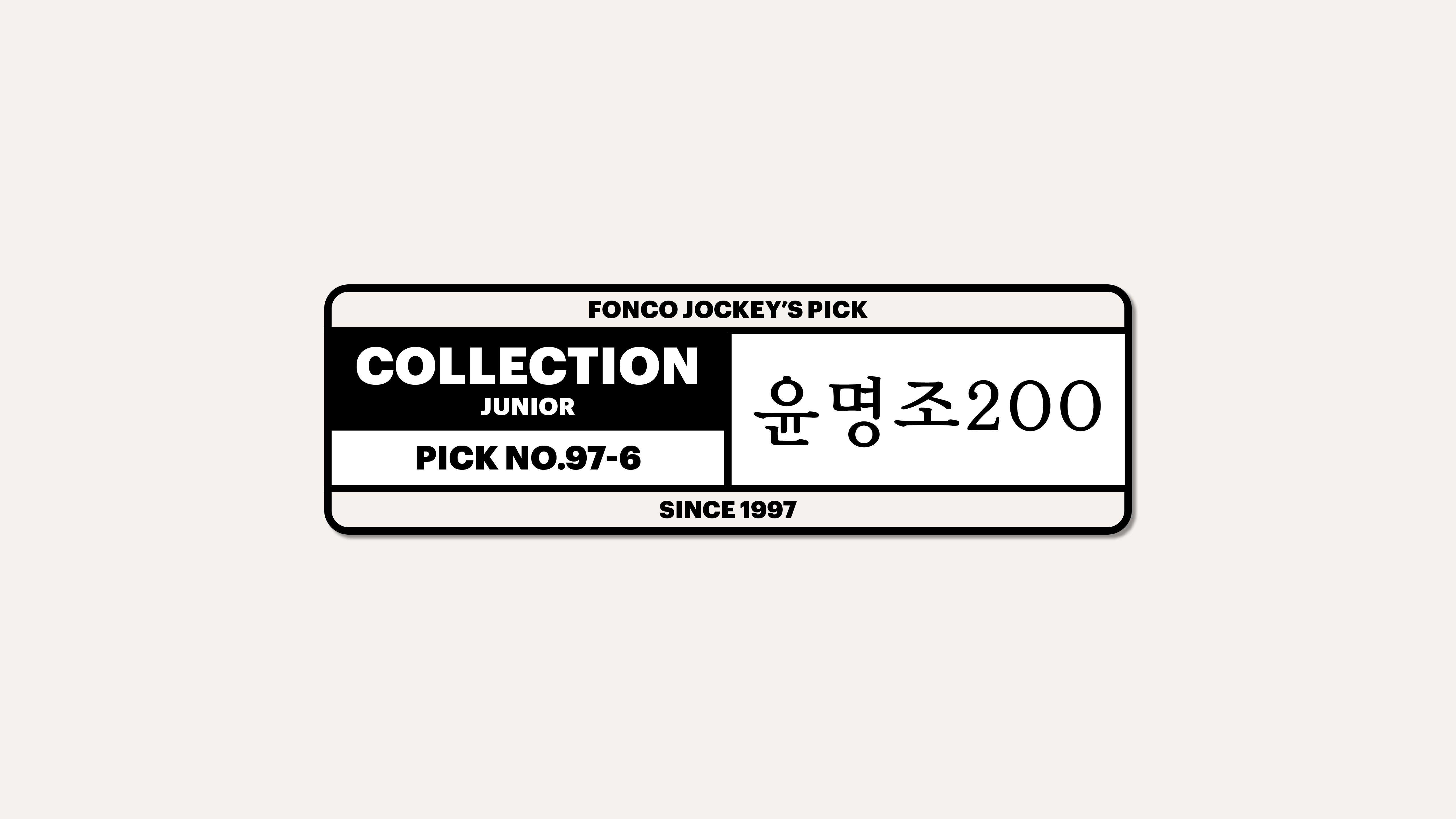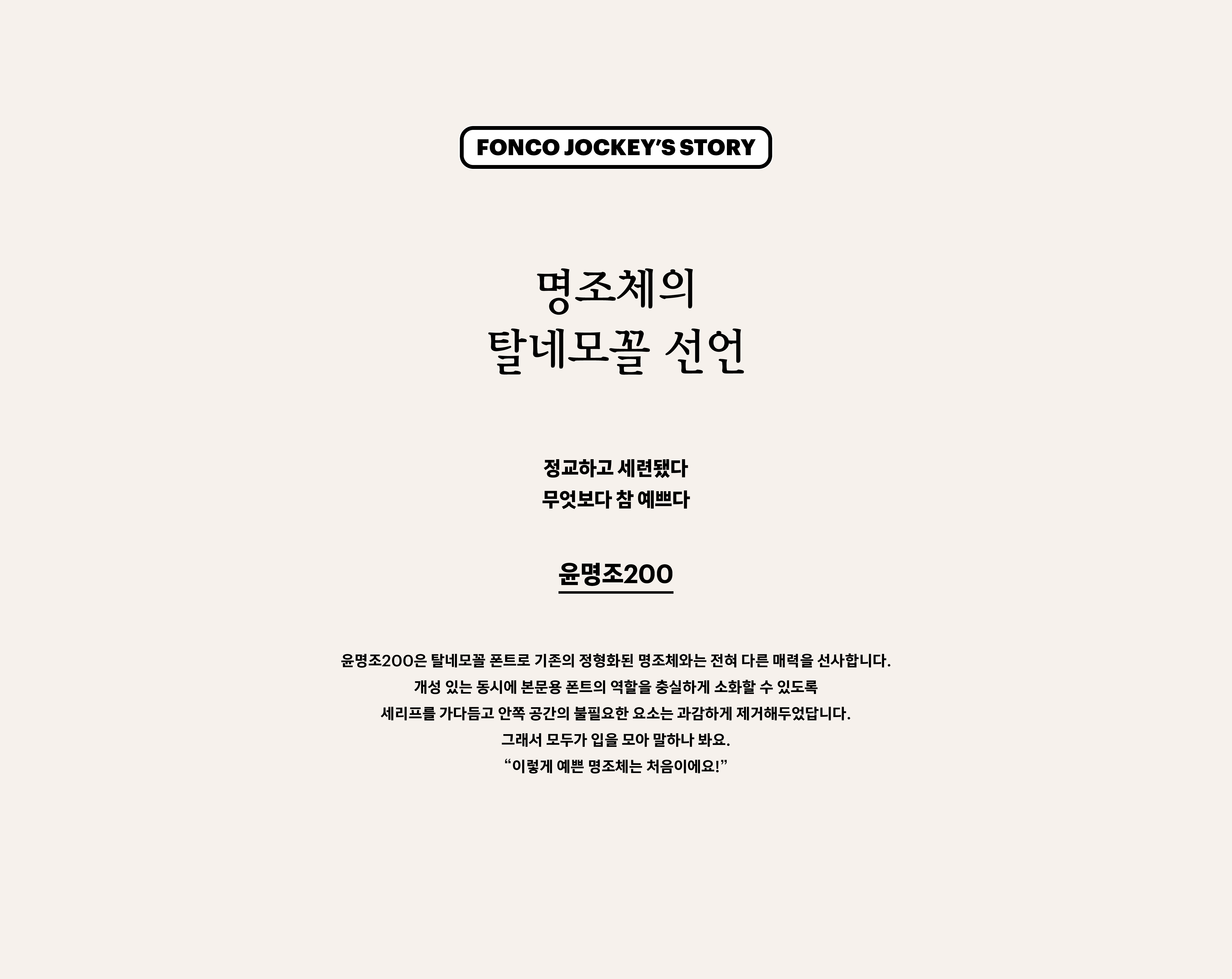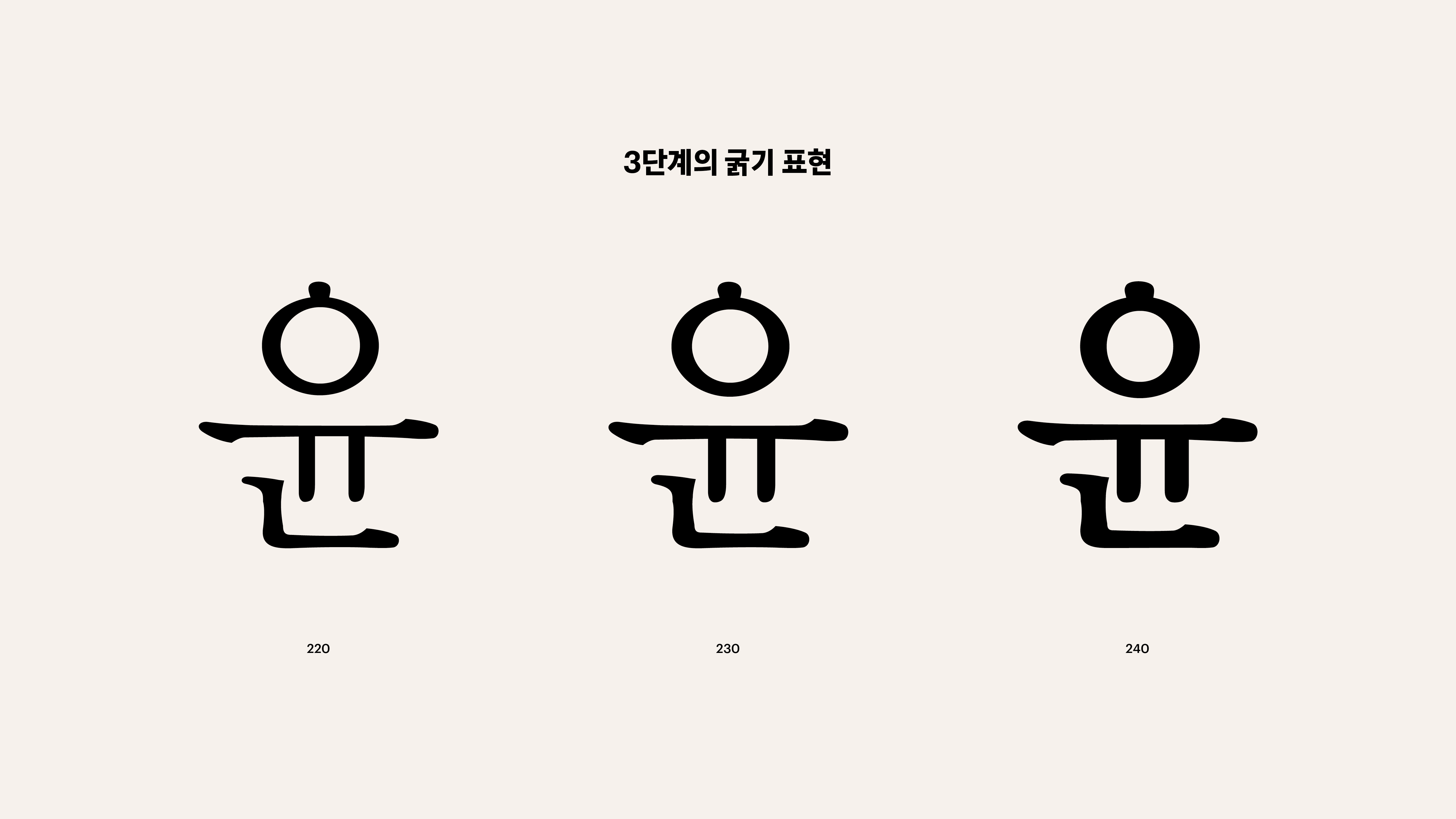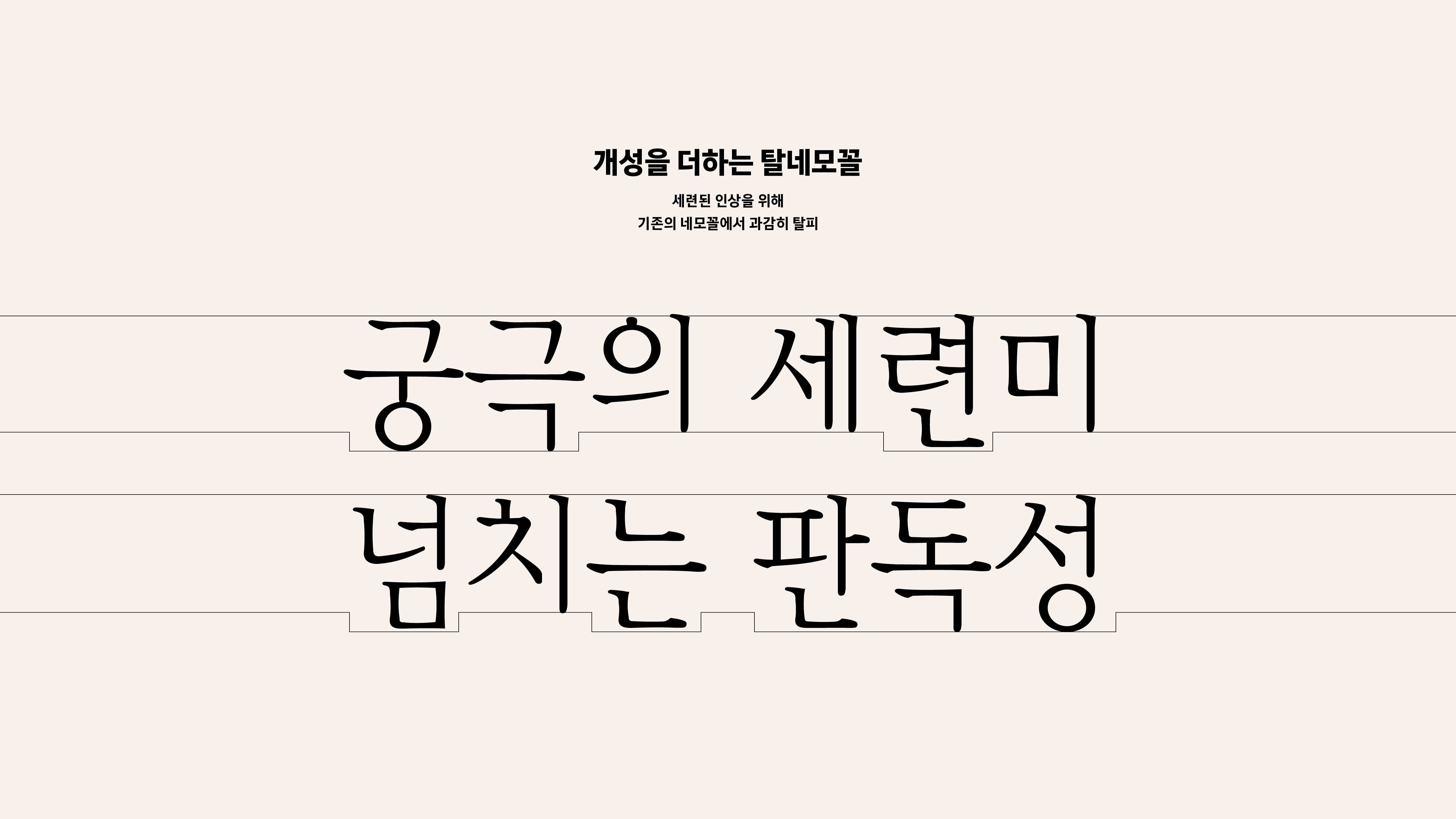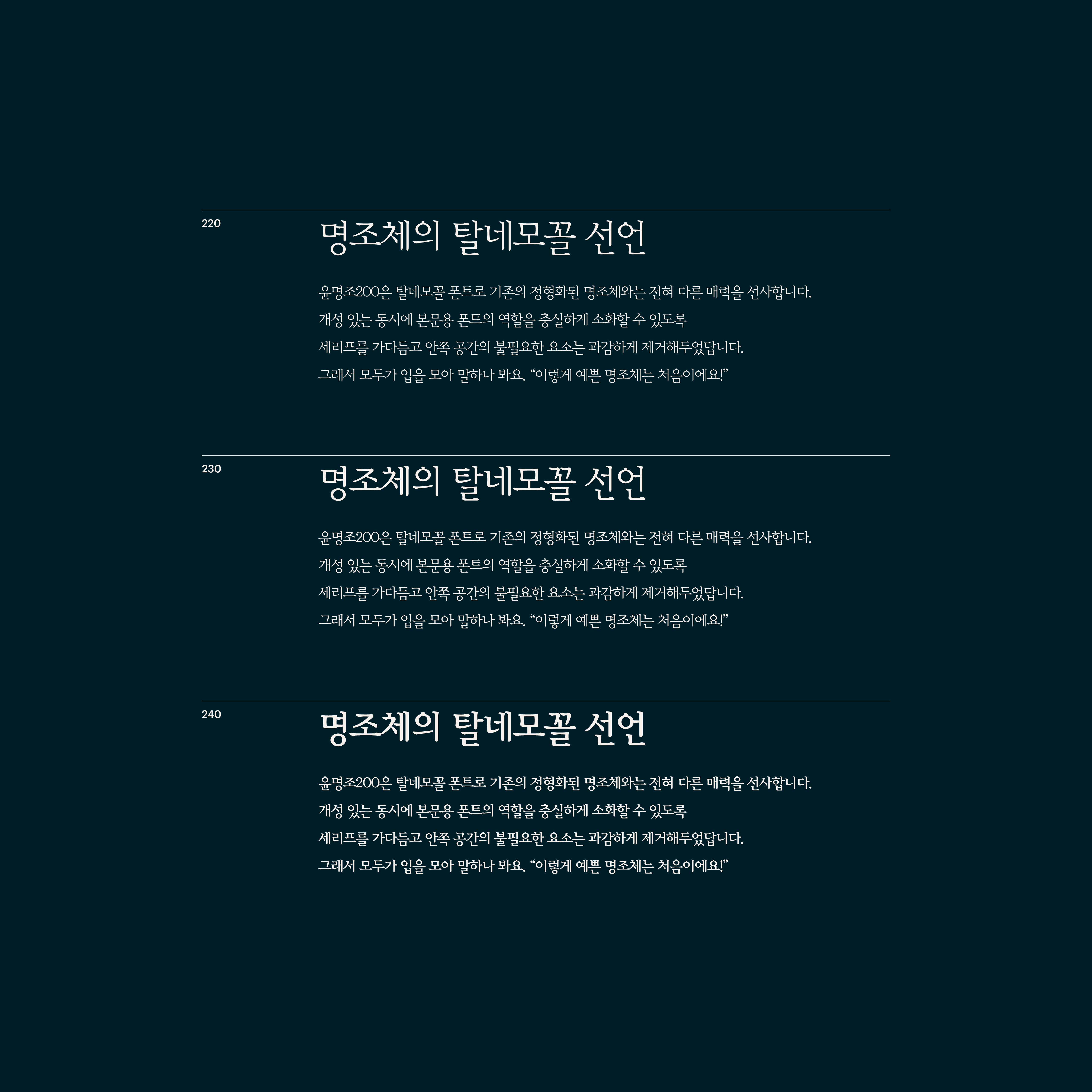
윤명조200은 탈네모꼴 폰트로 기존의 정형화된 명조체와는 전혀 다른 매력을 선사합니다. 본문용 글꼴의 역할을 충실하게 소화할 수 있도록 부리와 안쪽 공간의 불필요한 요소를 과감하게 제거하고, 깔끔하게 정돈해두었습니다. 덕분에 그 어떤 폰트보다 시원하게 탁 트인 느낌을 선보이지요. 앗, 가장 중요한 사실을 빼먹을 뻔했어요. 이렇게 예쁜 명조체는 정말이지 처음이라는 사실!
Yoon 윤명조 200